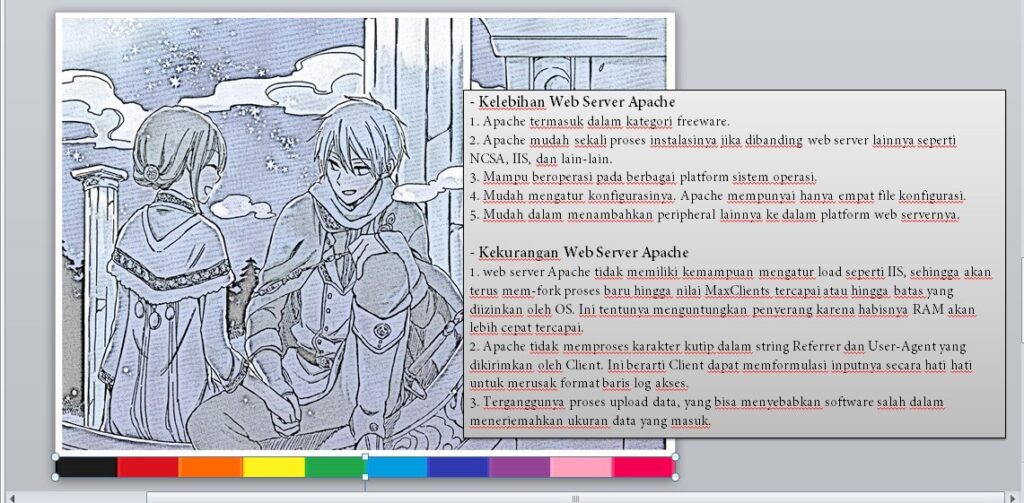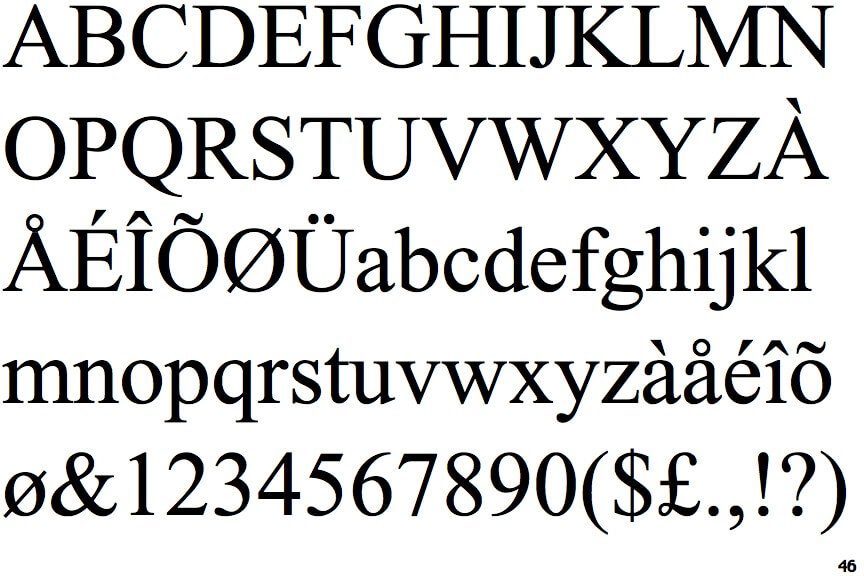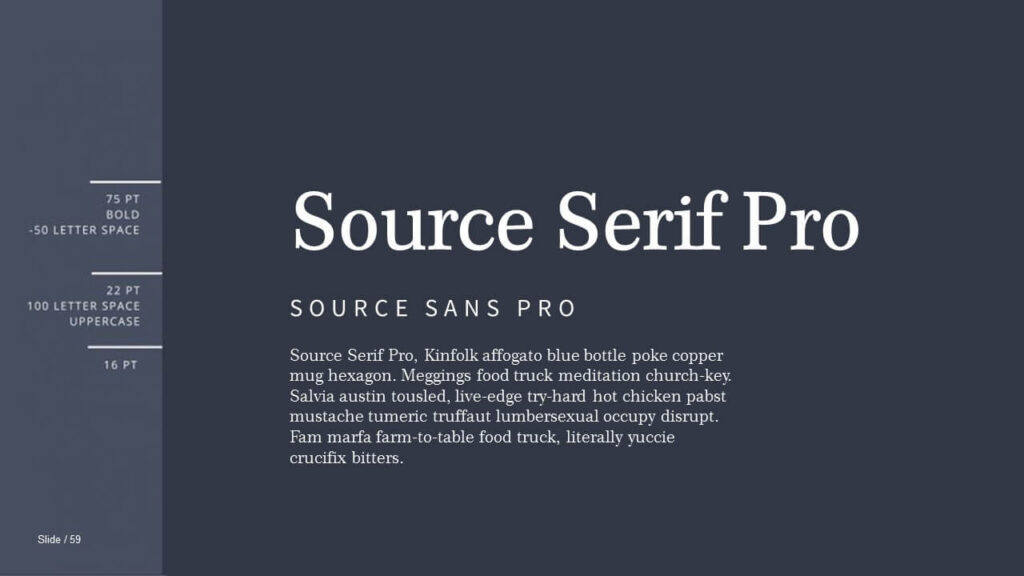
30 Font yang Bagus untuk PPT 2024: Font Presentasi PowerPoint – Berikut adalah contoh satu slide presentasi yang sering kita temui. Beberapa dari Anda mungkin berfikir tidak ada yang salah dalam slide itu. Akan tetapi, ini sebenarnya kesalahan yang selalu dilakukan berulang-ulang karena tidak menyadarinya.
Gambar 1. Contoh font yang tidak ideal dalam slide presentasi
Satu slide dengan konten yang lumayan padat disajikan dalam satu jenis font. Tanpa disadari, ketika Anda menampilkan slide seperti ini, Anda menawarkan informasi yang membuat audience malas membaca, sakit mata, atau bahkan tak sudi mendengarkan presentasi hanya karena font saja.
Ingat, esensi dari slide adalah membantu menyampaikan poin yang ingin disampaikan. Bukan menampilkan semua hal termasuk kata-kata yang ingin disampaikan oleh presenter sendiri.
Menyampaikan poin dalam slide tentunya dimulai dari font yang akan dipilih. Meskipun hal yang disampaikan banyak seperti gambar diatas, slide akan tetap terlihat bagus dan gampang dimengerti oleh audience ketika font yang dipilih sudah tepat.
Nah, Bagaimana Memilih Font yang Cocok untuk Presentasi Power Point?
Sebelum itu, ada dua macam jenis font. Serif dan San Serif. Jenis Serif adalah Font yang memilik buntut yang mudah dibaca dan sering dipakai di Buku, Majalah, dan tulisan-tulisan awam lainnya. Contohnya adalah font Times New Roman.
Gambar 2. Jenis font Serif
Sebaliknya, font jenis San Serif tidak memiliki buntut, bentuknya tegas dan sering dipakai ketika text berukuran besar yang ingin dilihat dari jauh. Contohnya adalah font Century Gothic.
Gambar 3. Jenis font San Serif
Memilih font yang cocok untuk presentasi power point untuk slide presentasi adalah dengan menggabungkan dua jenis font ini dalam satu slide yang sama. Ini guna membuat audience Anda bisa lebih mengerti dari segi konten, menjaga nuansa estetik yang dihasilkan dari kombinasi font ini.
Selain dari jenis font, yang perlu diperhatikan adalah ukurannya. Banyaknya konten membuat ukurun dipaksa harus kecil dan tanpa disadari membuat slide presentasi Anda jauh dari kata efektif. Penggunaan ukuran font sangan krusial untuk diperhatikan.
Gambar 4. Contoh kombinasi font ideal untuk slide presentasi
30 Font yang Bagus untuk PPT 2024: Font Presentasi PowerPoint
Memilih font untuk presentasi PowerPoint (PPT) adalah langkah penting dalam memastikan pesan Anda tersampaikan dengan baik. Font yang tepat dapat membuat slide Anda terlihat lebih profesional, mudah dibaca, dan menarik bagi audiens. Berikut ini adalah 30 font yang bagus untuk PPT di tahun 2024.
1. Roboto
Roboto adalah font sans-serif yang populer karena kombinasi antara ketebalan dan kejelasan hurufnya. Font ini sangat cocok untuk judul maupun teks utama.
2. Open Sans
Open Sans memiliki tampilan yang bersih dan modern. Font ini sering digunakan karena mudah dibaca di berbagai ukuran layar.
3. Montserrat
Montserrat adalah font untuk PPT yang bagus dengan karakteristik yang tegas dan elegan. Font ini sangat cocok untuk digunakan pada judul dan subjudul.
4. Lato
Lato menawarkan kesan profesional dan bersahabat, menjadikannya pilihan yang ideal untuk teks panjang maupun pendek dalam slide PPT.
5. Raleway
Raleway adalah font sans-serif dengan desain yang stylish. Cocok untuk presentasi yang ingin menonjolkan estetika modern dan minimalis.
6. Calibri
Calibri adalah font default di Microsoft Office yang terkenal dengan kesederhanaannya. Font ini tetap menjadi pilihan yang aman dan efektif untuk presentasi.
7. Poppins
Poppins menawarkan bentuk huruf yang bulat dan modern. Font ini memberikan kesan segar dan cocok untuk presentasi yang dinamis.
8. Avenir
Avenir adalah font yang elegan dan bersih, ideal untuk presentasi yang membutuhkan sentuhan profesional dan mewah.
9. Proxima Nova
Proxima Nova adalah font modern yang populer di kalangan desainer. Font ini menghadirkan kesan yang profesional dan mudah dibaca.
10. Helvetica
Helvetica adalah salah satu font klasik yang tetap relevan hingga saat ini. Font ini menawarkan kesederhanaan dan keterbacaan yang tinggi.
11. Nunito
Nunito adalah font sans-serif yang halus dan ramah di mata. Font ini ideal untuk presentasi yang membutuhkan teks yang mudah dibaca.
12. Playfair Display
Playfair Display memberikan sentuhan elegan dengan gaya serif-nya yang unik. Cocok untuk judul atau subjudul yang ingin menonjol.
13. Merriweather
Merriweather adalah font serif yang mudah dibaca, bahkan dalam ukuran kecil. Font ini memberikan kesan tradisional namun tetap modern.
14. Source Sans Pro
Source Sans Pro adalah font open-source yang sangat populer. Font ini cocok untuk presentasi yang membutuhkan keterbacaan tinggi.
15. Bebas Neue
Bebas Neue adalah font sans-serif dengan huruf kapital semua. Cocok untuk judul yang ingin terlihat kuat dan mencolok.
16. Oswald
Oswald adalah font sans-serif yang dikompresi secara vertikal, menjadikannya ideal untuk teks dalam ruang yang sempit.
17. Garamond
Garamond adalah font serif yang klasik dan elegan. Cocok untuk presentasi yang formal atau akademis.
18. Futura
Futura menawarkan desain geometris yang modern. Font ini sangat serbaguna dan bisa digunakan untuk berbagai jenis presentasi.
19. Georgia
Georgia adalah font serif yang dirancang khusus untuk keterbacaan di layar. Cocok untuk teks panjang di presentasi.
20. Century Gothic
Century Gothic menawarkan desain yang bersih dan sederhana dengan sentuhan modern. Ideal untuk judul dan teks singkat.
21. PT Sans
PT Sans adalah font yang modern dan fungsional, menawarkan keterbacaan yang baik di berbagai ukuran.
22. Verdana
Verdana adalah font sans-serif yang dikenal dengan keterbacaan yang tinggi, bahkan dalam ukuran kecil.
23. Arimo
Arimo adalah alternatif font keren untuk presentasi PPT selain Arial, dengan tampilan yang lebih modern dan dinamis.
24. Libre Franklin
Libre Franklin adalah font sans-serif yang memberikan kesan modern dan formal. Cocok untuk presentasi bisnis.
25. Ubuntu
Ubuntu adalah font keren untuk presentasi yang dikembangkan untuk sistem operasi Linux, tetapi kini menjadi pilihan populer karena bentuknya yang unik dan mudah dibaca.
26. Quicksand
Quicksand adalah font sans-serif dengan bentuk yang bulat dan ringan. Ideal untuk presentasi yang ingin menyampaikan kesan santai dan ramah.
27. Raleway Dots
Raleway Dots adalah variasi dari Raleway dengan tampilan yang unik. Cocok untuk slide yang ingin menonjolkan kreativitas.
28. Comfortaa
Comfortaa adalah font sans-serif dengan bentuk huruf yang membulat dan modern. Cocok untuk presentasi yang ingin terlihat santai namun profesional.
29. Titillium Web
Titillium Web adalah font yang modern dan ramping. Cocok untuk presentasi yang ingin terlihat minimalis dan elegan.
30. Teko
Teko adalah font sans-serif dengan bentuk yang tinggi dan sempit. Cocok untuk judul atau teks yang ingin terlihat mencolok dan berbeda.
Dengan menggunakan 30 font yang cocok untuk presentasi PowerPoint ini, Anda dapat meningkatkan kualitas visual presentasi Anda di tahun 2024. Pilihlah font bagus untuk presentasi yang sesuai dengan tema dan audiens presentasi Anda untuk menciptakan dampak yang maksimal.
Selamat mengaplikasikan dan membuat slide presentasi yang hebat dimulai dari cara memilih font yang bagus untuk ppt ini.